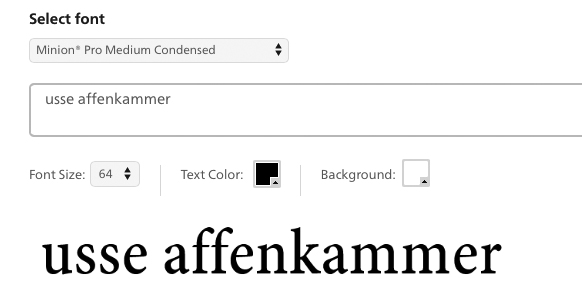
Versalien mit Schnörkel: Type oder selbstgemacht?
kennt jemand von euch diese Schrifttype oder wurden die Schnörkel vielleicht händisch eingefügt?
Welche Schrift ist dann die Grundlage?
Ich kann mir nicht vorstellen, dass diese Schnörkel an die Buchstaben gehören, das wurde ganz sicher nachträglich hinzugefügt. Und die serifenlosen Buchstaben S und W gehören auch nicht zu den restlichen Buchstaben, die aus einer ganz anderen, serifenhaltigen Schriftart stammen.
Und die serifenlosen Buchstaben S und W
Ach was, bei denen sind doch ganz offensichtlich die Serifen nur 'n büschn verrutscht und verbogen ... ;-)
Da wären wir ja mit Schokoladenspänen vermutlich schon wieder bei der richtigen Assoziation, wenn man den Namen bedenkt.